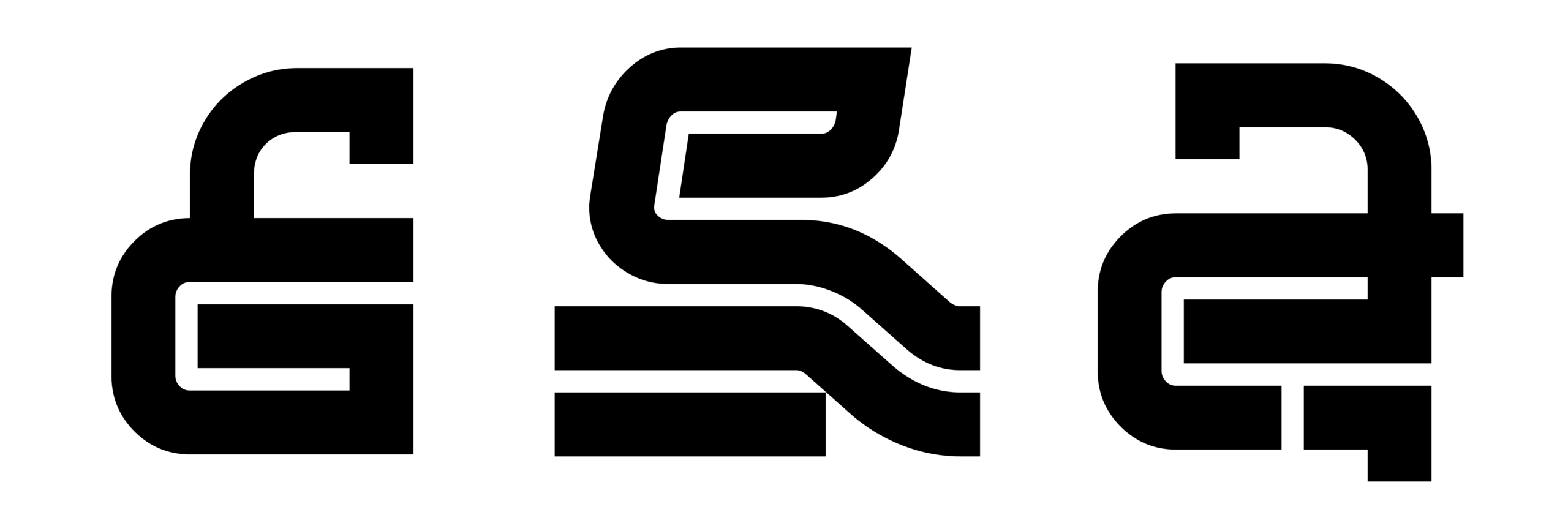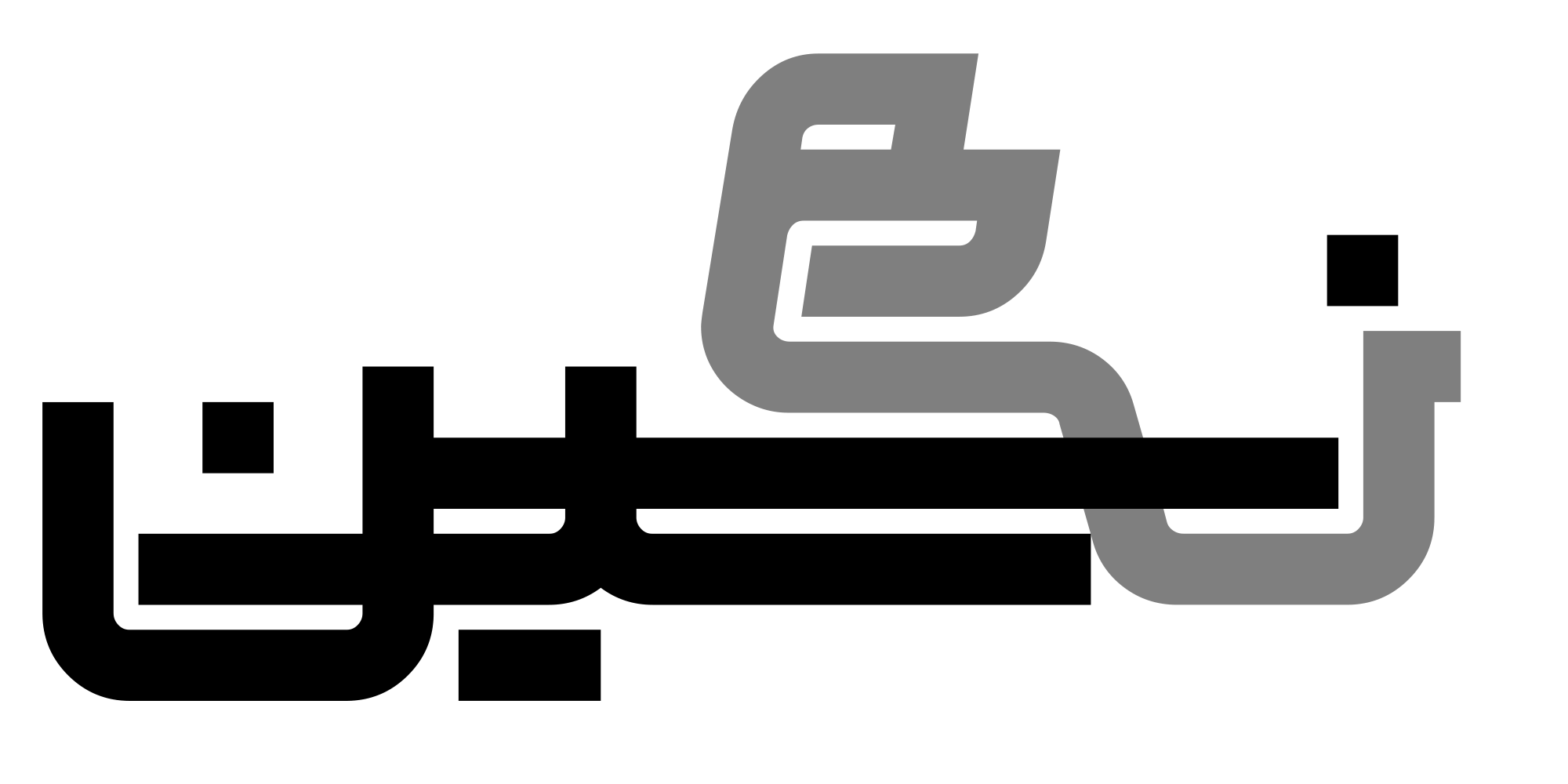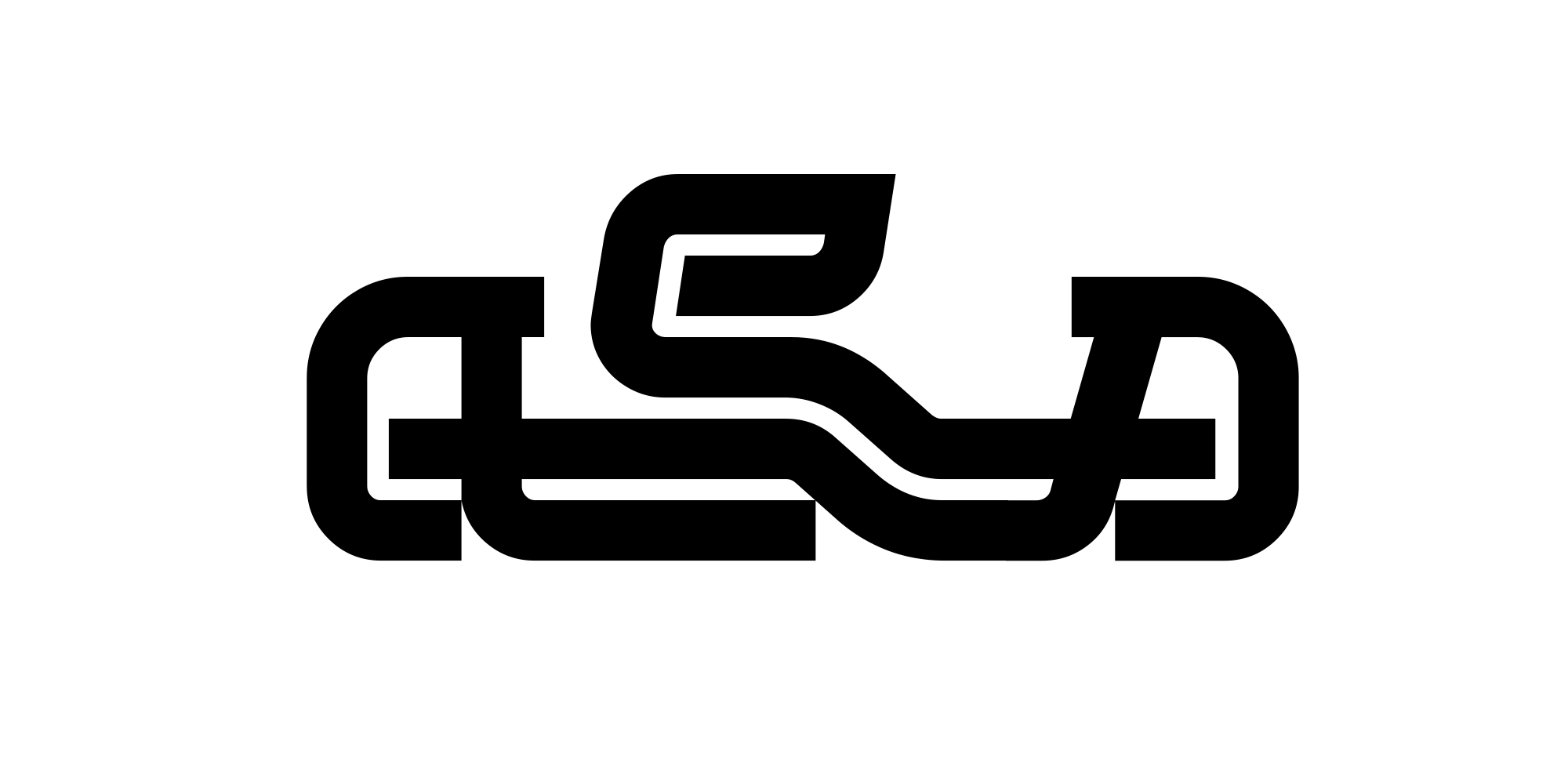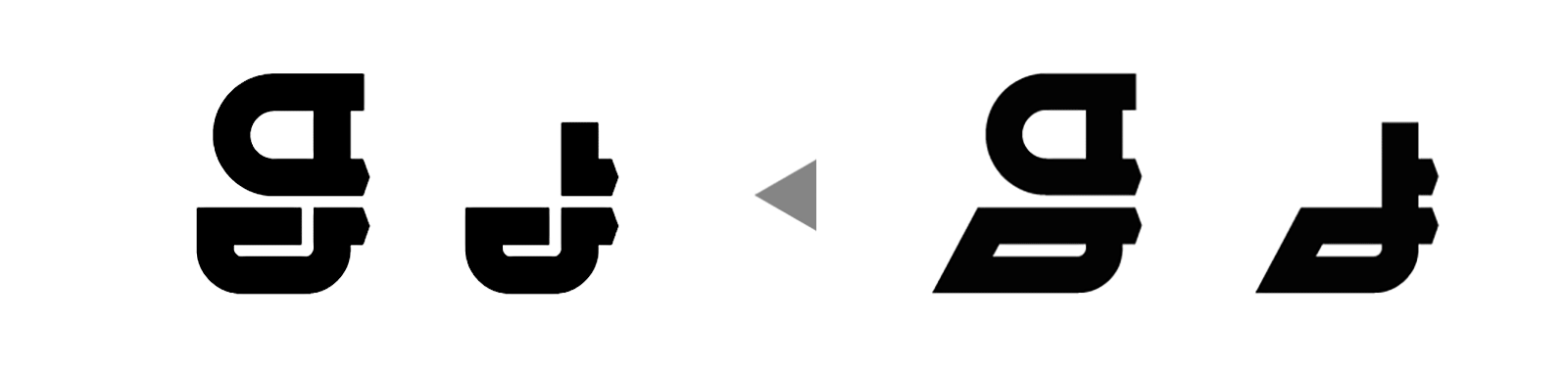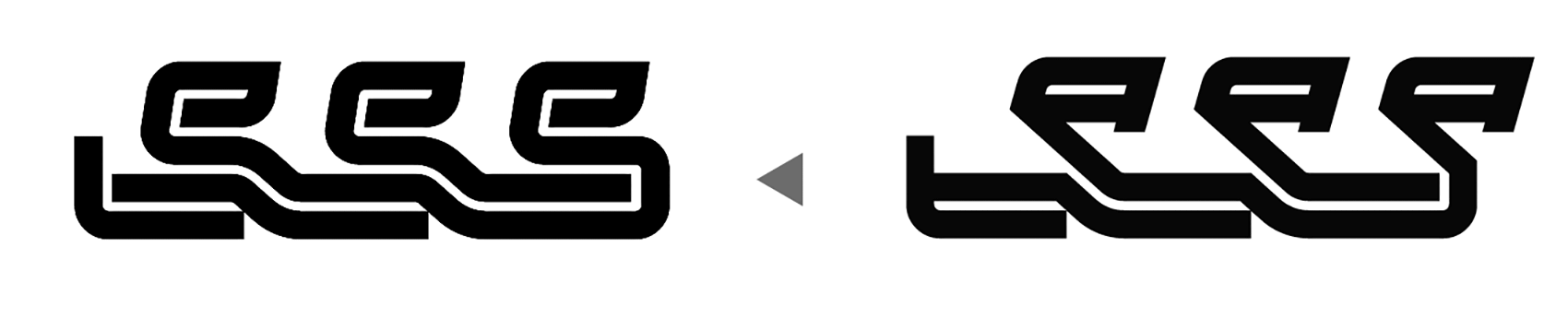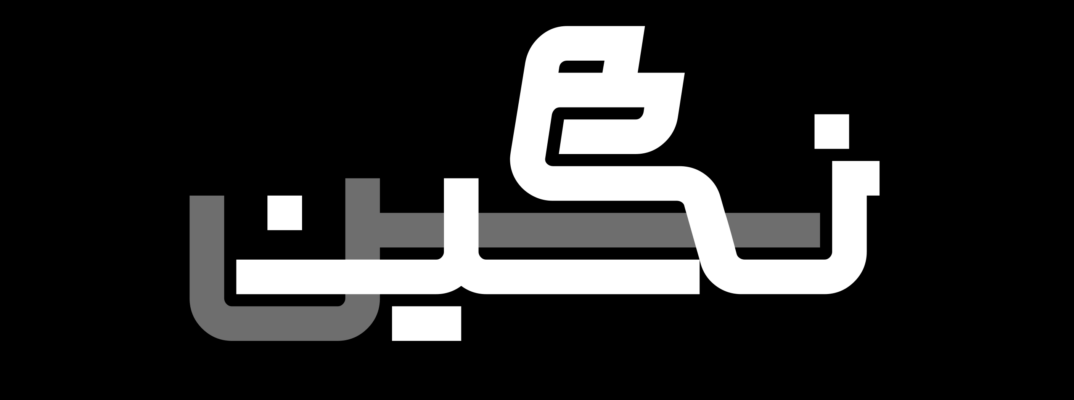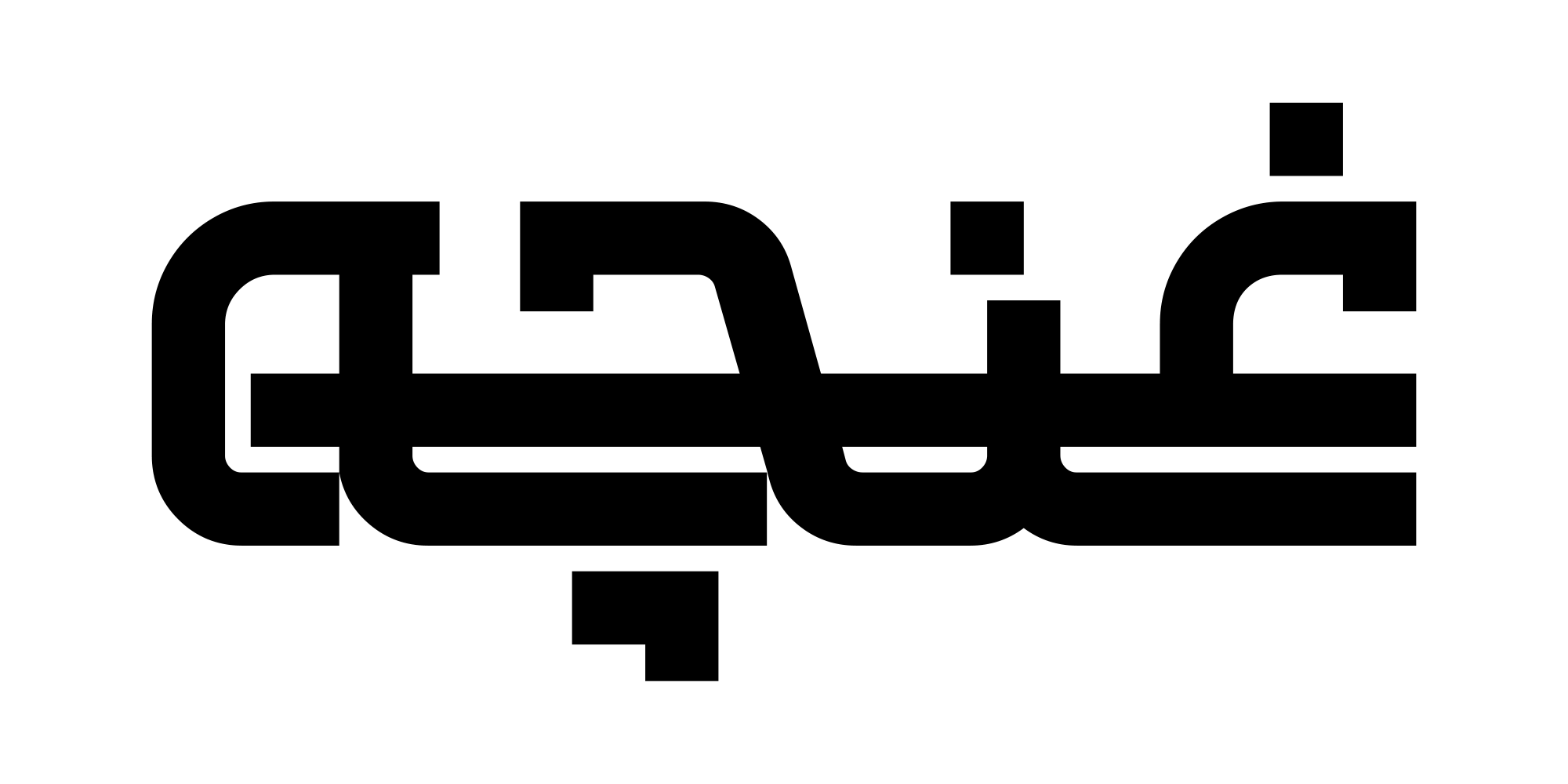
فونت تکنو؛ نگاهی به فرایند و منطق طراحی
در روزهای ابتدایی انتشار فونت تکنو، شباهتهای ظاهری این فونت با یک لوگوتایپ باعث شد بخشی از توجهها از خود فونت و ویژگیهای طراحی آن دور شود و حاشیهها پررنگتر از فرآیند و ایدهی شکلگیری پروژه دیده شوند.
هدف از نوشتن این مطلب، ورود به این حاشیهها یا پاسخ مستقیم به نقدها نیست؛ بلکه تلاش میکنیم مسیر شکلگیری فونت تکنو، ایدهی اولیه و روند طراحی آن را شفافتر توضیح دهیم.
امیدواریم با توضیح فرآیند طراحی و نگاه جزئیتر به ساختار فونت، امکان قضاوت منصفانه درباره خود اثر فراهم شود.
شکلگیری ایده
فونت تکنو در قالب یکی از پروژههای دوره طراحی حروف «تایپتراپی» شکل گرفته است.
در این دوره، هنرجویان موظفاند در بازهای محدود، به یک ایدهی مشخص و قابل توسعه برسند؛ ایدهای که به ویژگیهای فرمی حروف مربوط است و در قالب یک «ژن» تعریف میشود.
برای رسیدن به این ژن، هنرجو مجموعهای از منابع را بررسی میکند، از جمله:
خوشنویسی فارسی و عربی
حروفنگاری معاصر
لوگوتایپهای فارسی
و فونتها و تایپفیسهای لاتین
هدف از این بررسیها، رسیدن به ساختاری است که:
قابل تحلیل باشد
متغیرهای ۱۵گانه را تعریف کند. (در دوره تایپتراپی، ۱۵متغیر تعریف میشود)
و امکان تکثیر و توسعه بر اساس همان متغیرها را فراهم کند
در طول مسیر طراحی، هنرجو بارها ژن اولیه را بازبینی و اصلاح میکند تا نتیجه نهایی، بهتدریج از منابع الهام فاصله بگیرد و به ساختاری مستقل برسد.
حروف دوخطی (Double-line type)
ایدهی اصلی فونت تکنو با بررسی فونتها و لوگوتایپهای طراحیشده در سبک دوخطی شکل گرفت.
در آغاز، تمرکز اصلی بر نسبت میان دو خط موازی در بخشهای ضخیم و تکخط شدن فرمها در قسمتهای نازک بود. نرگس همایون (طراح فونت تکنو) در این مرحله با استفاده از همین منطق، شکلهای تازهای از حروف را جستوجو میکرد؛ تجربههایی که در همان مراحل ابتدایی، ظرفیت ایده و توانایی طراح را نشان میدادند.
جابهجایی و گردش آگاهانهی خطوط، تعادل دقیقی میان فضای مثبت و منفی ایجاد کرده و با حداقل فرم، ساختار آشنای حروف را بازنمایی میکند.
اما بهتدریج مشخص شد که این ایده صرفاً در سطح طراحی تکحرفها متوقف نمیماند. در ادامهی روند طراحی، توجه از فرم منفرد حروف به رفتار آنها در کنار یکدیگر معطوف شد.
جابهجاییها و انفصالهای دو خط موازی باعث میشد امتداد یک حرف وارد فضای حروف مجاور شود و مرزهای متعارف میان حروف دچار تغییر شود.
در فونت تکنو، امتداد و تداوم خطوط با اصل «پیوستگی» در گشتالت منطبق است؛ چشم بهجای حرکت خطی و حرفبهحرف از راست به چپ، در امتداد خطوط رفتوبرگشت میکند و کلمه را بهعنوان یک فرم درهمتنیده درک میکند.
در فونت تکنو، چشم فرم کلی کلمه را پیش از تفکیک حروف منفرد درک میکند. در نتیجه، فرایند خواندن در این فونت با الگوهای رایج در دیگر فونتها تفاوت دارد.
در خوشنویسی فارسی و عربی، مرز حروف همیشه بهصورت صریح و تفکیکشده تعریف نمیشود.
امتدادها، اتصالات و همنشینیها نقش مهمی در شکلگیری ترکیب دارند؛ ویژگیای که در فونتهای امروزی بهدلیل محدودیت سیستم حروفچینی، کمرنگ شده است.
فونت تکنو تلاش میکند بخشی از این کیفیت را نه از طریق ساخت ترکیبات (لیگچر)، بلکه از راه منطق ساختاری حروف و امتداد آنها در دل کلمه بازآفرینی کند؛ رویکردی متفاوت برای رسیدن به تجربهای آشنا.
در بهروزرسانی اخیر فونت تکنو، برخی اجزای مشخص مانند فرم سرکش «کاف» و پاشنه «واو» (و شکلهای مرتبط در سایر حروف) بازطراحی و جایگزین شدند. علاوه بر این با تغییراتی در اتصال و انفصالها، ساختار درهمتنیدهٔ حروف تقویت شد.
هدف اصلی از نگارش این شرح پروژه روشن کردن این نکته بود که مبنای شکلگیری یک تایپفیس، نه یک فرم اولیه، بلکه یک تفکر طراحی است؛ تفکری که باید بتواند در قالب یک سیستم پیچیده، صدها کاراکتر، اتصال و ترکیب را بهدرستی مدیریت کند. طراحی تایپفیس گسترش مکانیکی چند حرف به کل الفبا نیست، بلکه فرآیندی است که در آن ایدهی اولیه تنها نقطهی شروع است و شخصیت واقعی تایپفیس بهتدریج و در طول مسیر طراحی تثبیت میشود.
برخلاف تصور رایج، طراحی اولین حرف، سادهترین بخش این مسیر است. چالش اصلی از جایی آغاز میشود که هر حرف جدید باید با تمام حروف طراحیشدهی پیش از خود هماهنگ شود. این الزام، طراح را ناچار میکند بارها به مراحل قبلی بازگردد و حتی حروف بهظاهر حلشده را دوباره بازطراحی کند تا مسئلهی یک گلیف در کل سیستم برطرف شود.
در این مسیر، طراحی یک تایپفیس بیش از آنکه شبیه حرکتی خطی باشد، به صعودی تدریجی شباهت دارد؛ آغاز راه را بسیاری میتوانند طی کنند، اما طراحی موفق آن است که بتواند این مسیر را تا قله ادامه دهد و به نتیجه برساند.
در پروژههای تایپتراپی، انتخاب یک لوگوتایپ یا طرح آماده بهعنوان نقطهی شروع، با این هدف انجام میشود که زمان کمتری صرف جستوجوی ایدهی اولیه شود و هنرجو سریعتر وارد فرایند طراحی گردد. در تایپتراپی، تمرکز اصلی دوره نه بر خود ایدهی اولیه، بلکه بر یادگیری کار منظم، مدیریت فرایند طراحی و رساندن یک پروژهی پیچیده به نتیجه است؛ مهارتهایی که در نهایت نقش تعیینکنندهتری در طراحی یک تایپفیس دارند.
فونت تکنو یک پروژه مطالعاتی است که در چارچوب یک دوره آموزشی و با هدف تجربه و یادگیری شکل گرفته است.
انتشار این فونت در فروشگاه، صرفاً با هدف ارائه رسمی از طریق یک کانال معتبر انجام شده و نه بهعنوان پروژهای با اهداف تجاری.
امیدواریم با دیده شدن این شرح، توجه دوباره به خود فونت و امکانات آن بازگردد و قضاوتها بر اساس آنچه واقعاً طراحی شده است، شکل بگیرند.